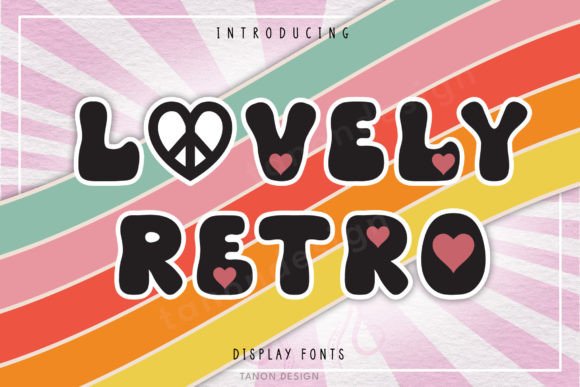
Lovely Retro
Lovely Retro – A Fonte Vintage Que Vai Encantar Seus Projetos
Se você está em busca de uma tipografia que traga o charme dos anos dourados ao mesmo tempo que celebra o romance do Dia dos Namorados, a Lovely Retro é a escolha perfeita. Desenvolvida com detalhes delicados e curvas elegantes, essa fonte vintage combina nostalgia e modernidade, tornando‑se indispensável para designers que desejam criar peças únicas e cheias de personalidade.
Por que escolher a Lovely Retro?
- Estilo autêntico vintage: Traços inspirados na tipografia dos anos 60‑70, com um toque romântico que evoca lembranças de cartas de amor antigas.
- Versatilidade total: Ideal para t‑shirts, canecas, convites, cartões, ilustrações digitais, artesanato e qualquer outro projeto criativo.
- Leitura fácil: Apesar do visual ornamental, a fonte mantém ótima legibilidade, perfeita para textos curtos e slogans impactantes.
Aplicações criativas que você pode explorar
- Design de camisetas: Crie estampas com frases românticas ou slogans divertidos usando a Lovely Retro para atrair olhares nas ruas e nas redes sociais.
- Canecas personalizadas: Combine a fonte com ilustrações de corações ou flores para vender produtos exclusivos em plataformas como Etsy e Redbubble.
- Cartões e convites: Dê um toque clássico a cartões de Dia dos Namorados, casamentos ou aniversários, destacando o texto principal com a Lovely Retro.
- Arte digital e prints: Use a fonte em mockups de posters, wallpapers ou quadros decorativos para ambientes vintage.
- Artesanato e scrapbooking: Imprima etiquetas, etiquetas de presente ou papel de embrulho com a Lovely Retro para projetos DIY memoráveis.
Lovely Retro não é apenas mais uma fonte; é uma ferramenta de storytelling visual que transforma projetos comuns em verdadeiras obras de arte retro‑românticas. Seja para vender produtos personalizados ou para dar vida a um projeto pessoal, esta fonte entrega qualidade, charme e versatilidade. Não perca tempo – baixe agora a Lovely Retro e eleve seu design a um novo patamar!